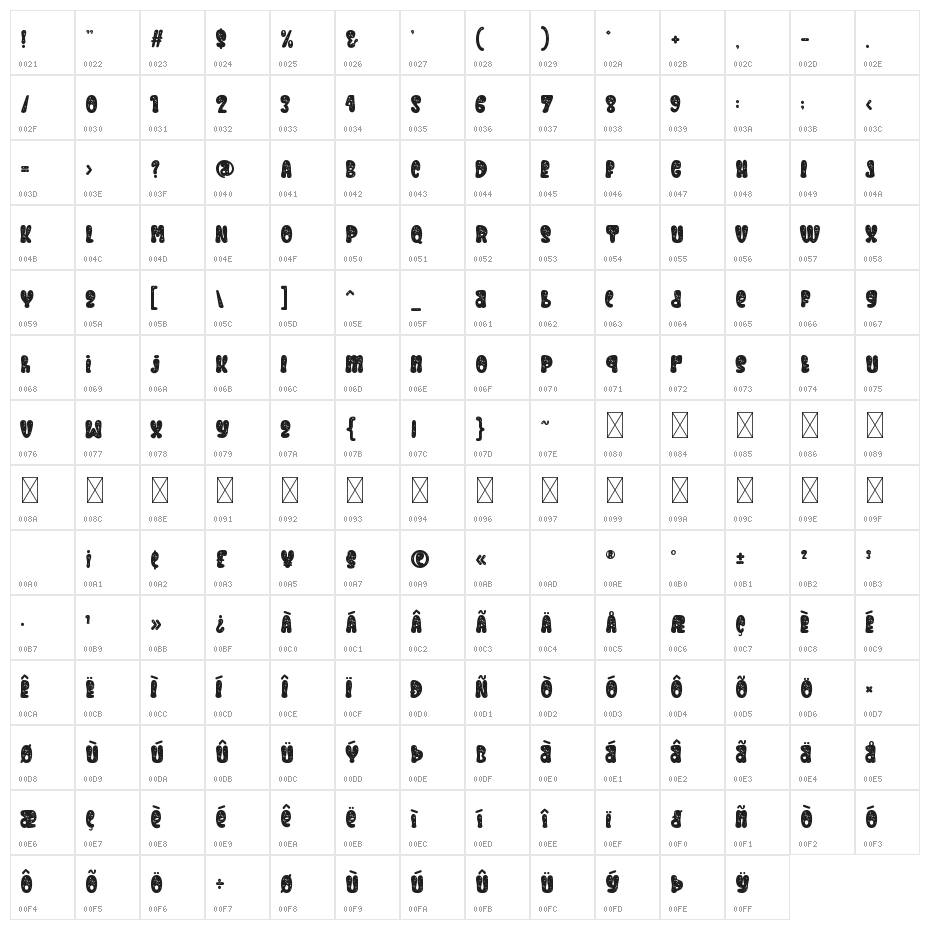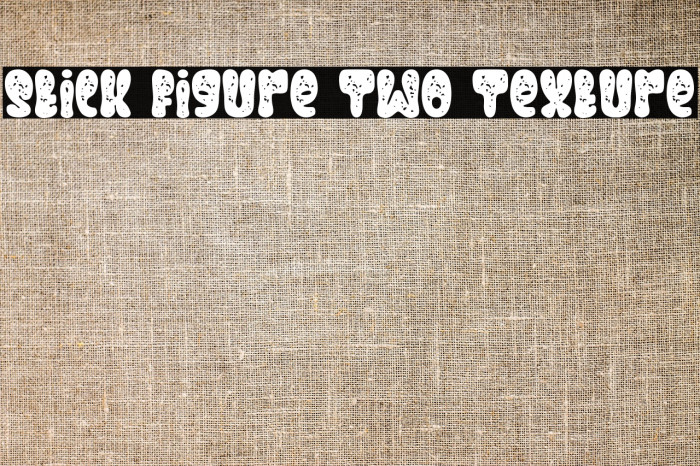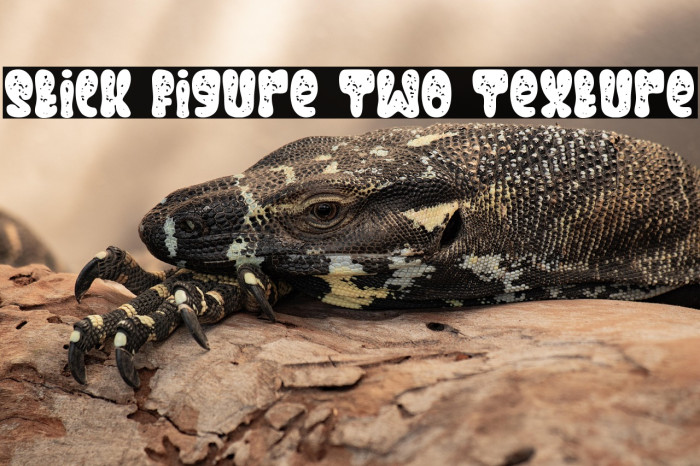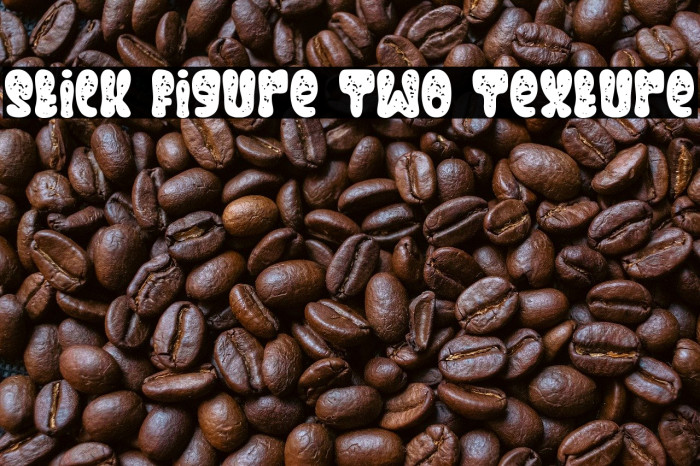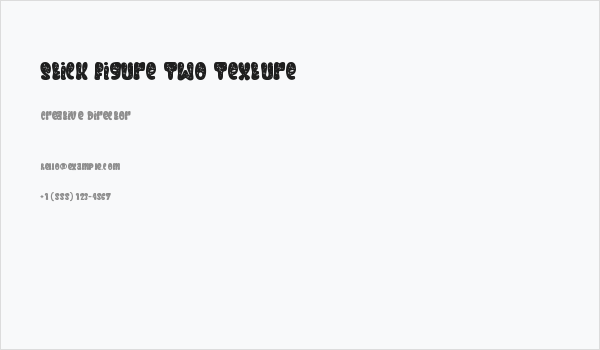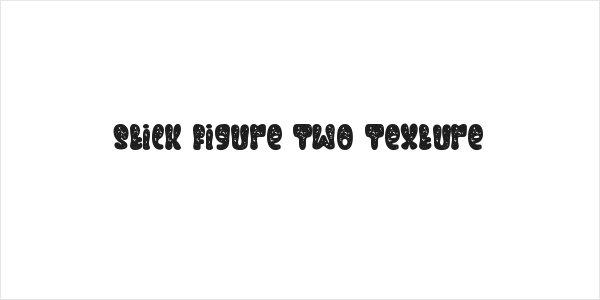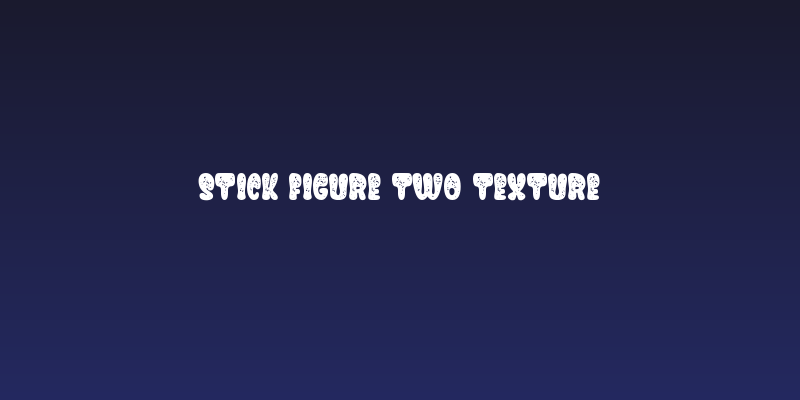
Stick Figure Two Texture Font
| Stile generale | Playful, Whimsical |
| Progetti proposti | Ideal for children's books, playful branding, party invitations, and creative posters. |